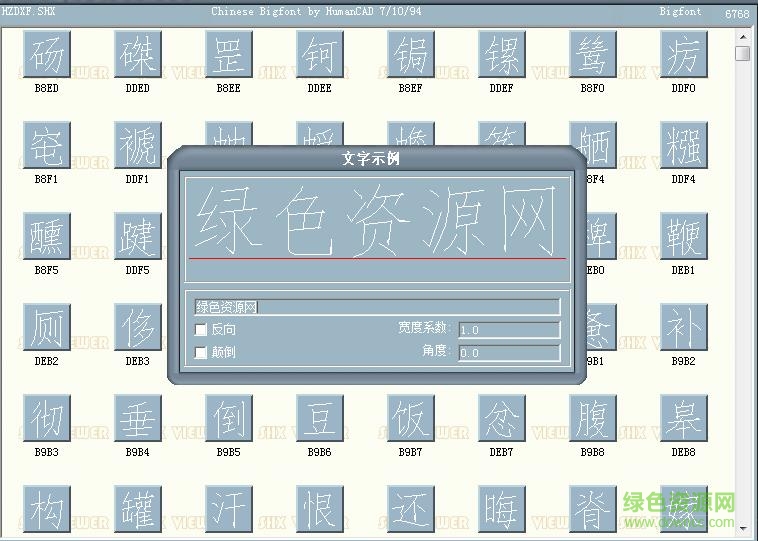
hzdxf.shx
hzdxf.shx小編點(diǎn)評(píng)
hzdxf.shx在行文結(jié)構(gòu)上擁有不錯(cuò)的筆鋒視覺效果,在cad制圖中輸入文字即能夠感受到棱角分明的字體所帶來的視覺美感!
hzdxf.shx字體介紹
1、等寬的txt字體。在這種字體中,除了分配給每個(gè)字符的空間大小相同(等寬)以外,其他所有的特征都與txt相同。因此,這種字體尤其適合于書寫明細(xì)表或在表格中需要垂直書寫文字的場合。
2、在cad制圖中能夠?qū)?shx字體進(jìn)行美觀的處理,讓你在屏幕上顯示的字體更加優(yōu)質(zhì)